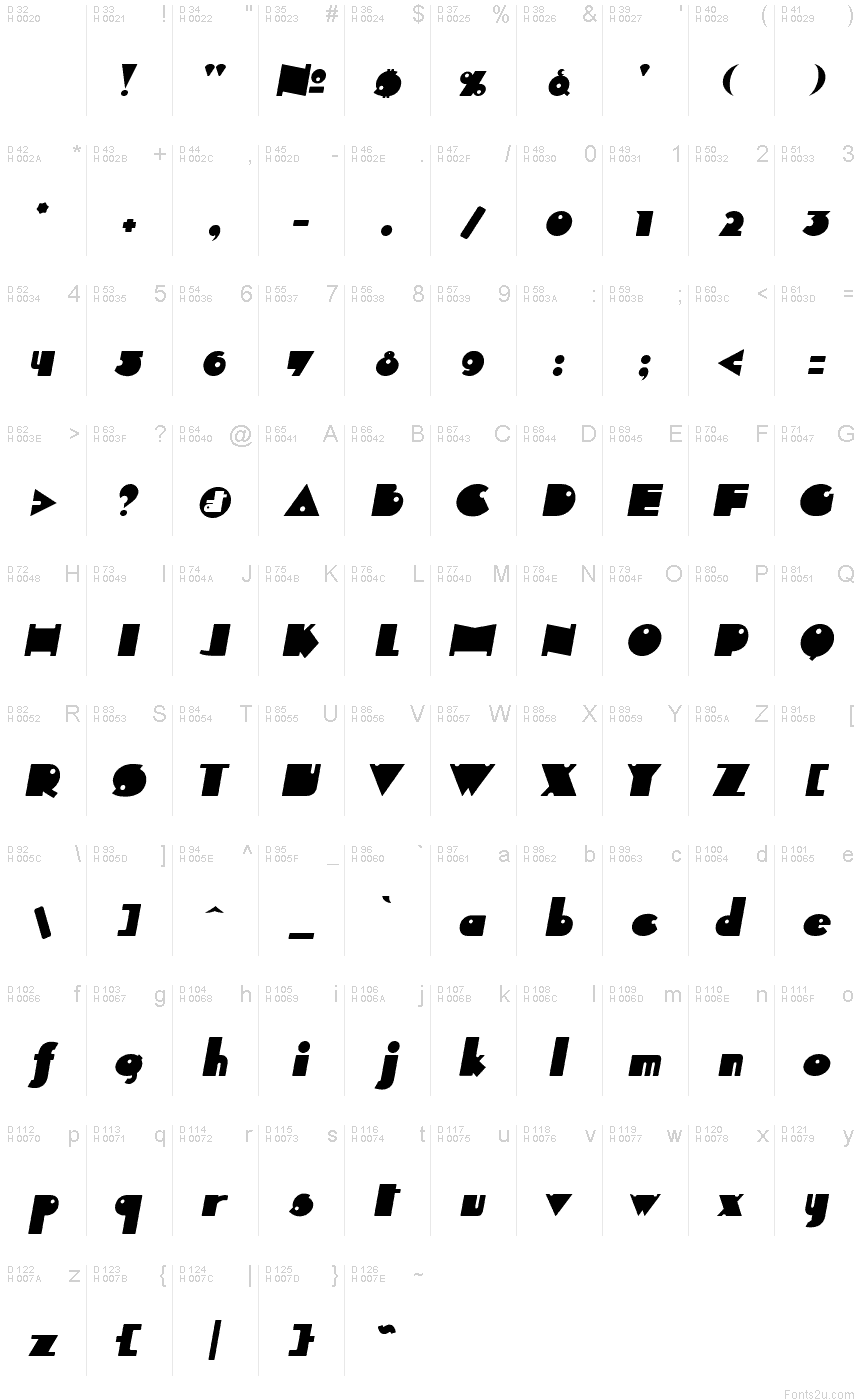
Independant Italic
Independant Italic od Phynette & Apostrophic Laboratories to darmowy krój typu display w stylu groovy, który wygląda, jakby został wycięty z czarnego, błyszczącego winylu. Każda litera pochyla się do przodu w odważny, zabawny sposób, a zaokrąglone, „wykrawane” oczka nadają całości klimat retro szyldów malowanych ręcznie. Odstępy są ciasne i pełne energii, dzięki czemu słowa na stronie wyglądają, jakby się toczyły, zamiast nieruchomo spoczywać.
Independant Italic sprawia, że nagłówki na plakatach, opakowaniach, ulotkach, grafikach muzycznych, logotypach i stronach internetowych natychmiast przyciągają wzrok. Ten darmowy font świetnie sprawdza się w dużych rozmiarach, gdzie jego wyraziste krzywizny i kropki zachowują ostrość i czytelność. W przypadku mniejszych tekstów zestaw go z czystym, geometrycznym bezszeryfowym krojem, aby pozwolić jego groovy charakterowi zaistnieć bez przytłoczenia projektu.